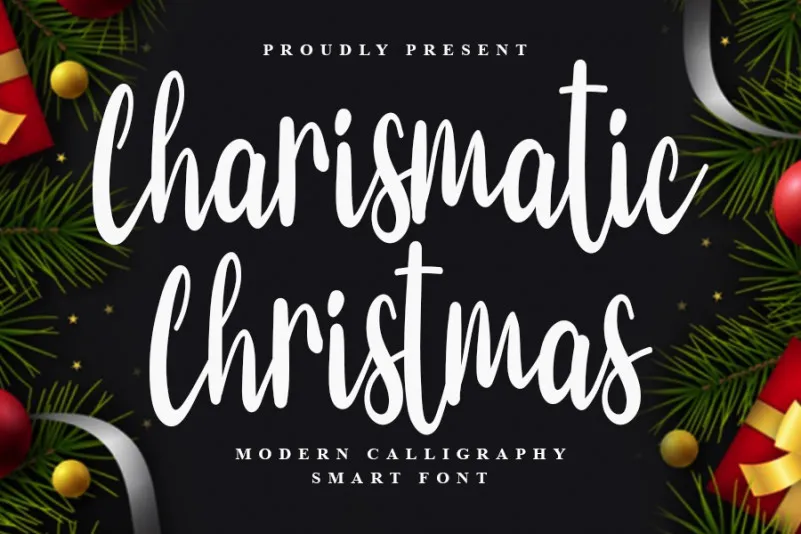
Charismatic Christmas Script Font – Fonte Grátis
Charismatic Christmas Script Font
A fonte Charismatic Christmas Script é uma elegante escolha para aqueles que buscam expressar o espírito natalino com estilo. Com seus traços fluidos e alegres, esta fonte script atinge o ponto certo entre delicadeza e energia vibrante. O fato de ter um baseline dançante adiciona ainda mais personalidade e emoção a qualquer design que você criar. Seja para cartões de Natal criativos ou até mesmo para gráficos de sala de estar com decorações natalinas, Charismatic Christmas Script trará sua arte à vida com uma pitada de festividade inegável. Ideal tanto para quem busca um toque especial quanto para aqueles que buscam adicionar um pouco mais de emoção em suas criações, esta fonte é uma excelente escolha.